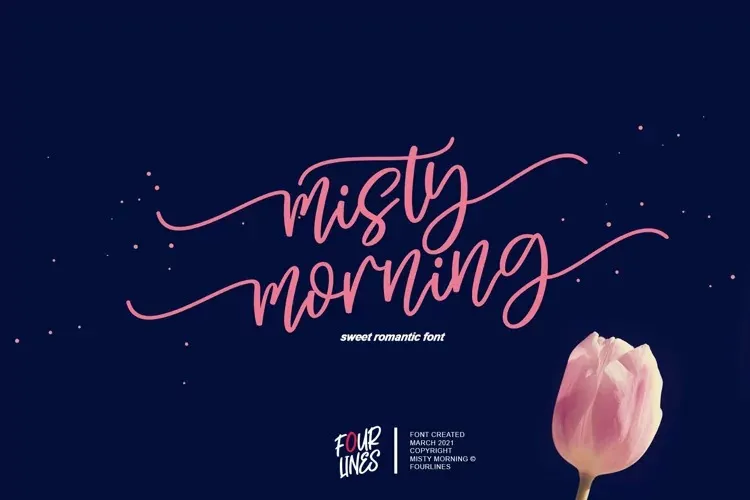
Misty Morning Font – Download Grátis
A fonte Misty Morning Font é uma elegante escolha para designers que procuram um estilo delicado e versátil. Ela foi criada por designer fourlines.studio, disponível no site de design 99designs. Esta script font não apenas adicionará um toque romântico a seu próximo projeto, mas também garantirá que suas criações se destaquem. Com sua elegância perfeita para qualquer aplicação, seja em logomarcas, convites de casamento ou até mesmo camisetas personalizadas, Misty Morning Font é uma fonte que você quer ter sempre à mão. Seu estilo único e versátil a torna o tipo perfeito para criar designs memoráveis e inovadores. Experimente Misty Morning Font e inspire-se com sua capacidade de moldar qualquer projeto digital em um trabalho de arte excepcional.